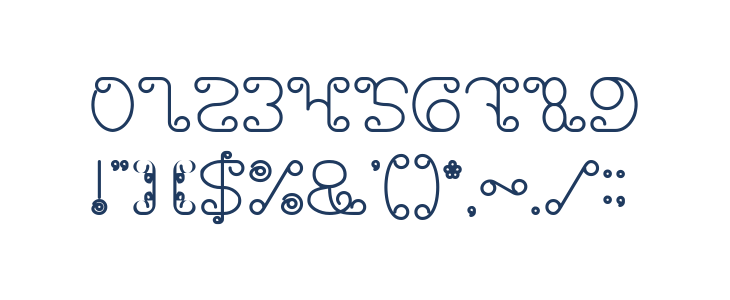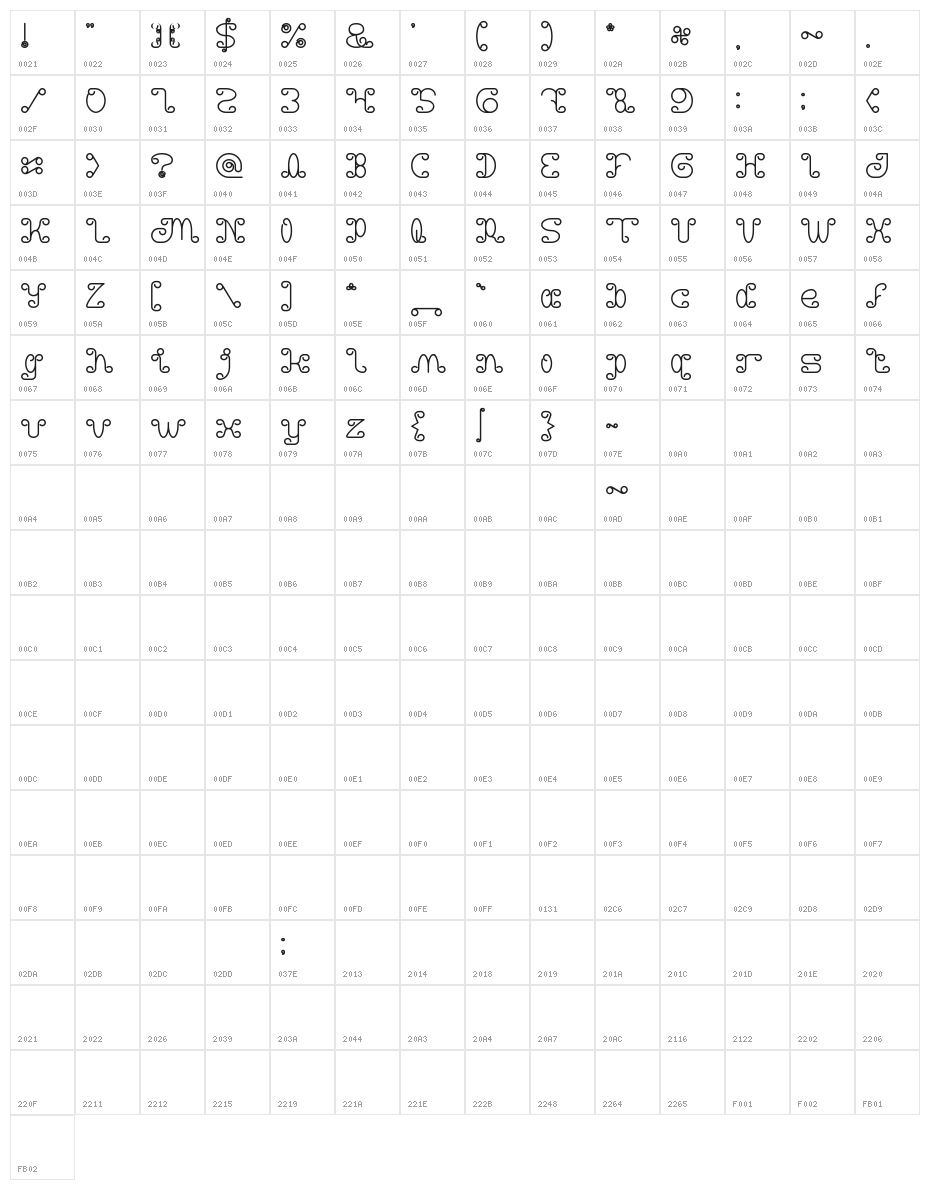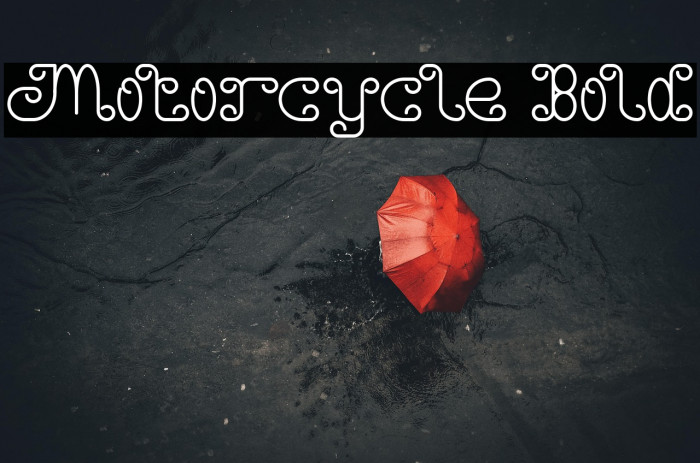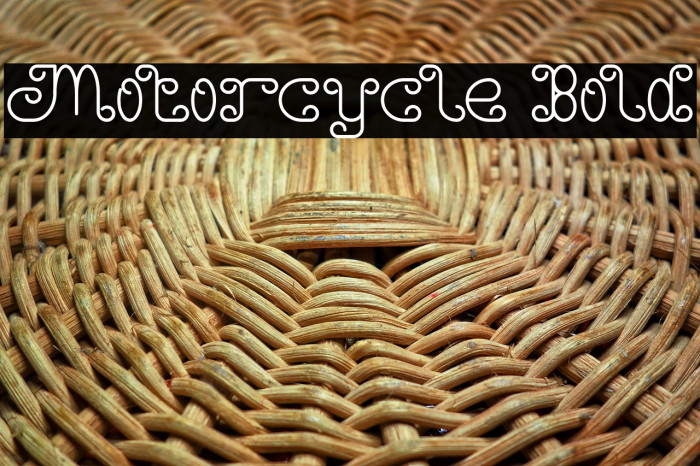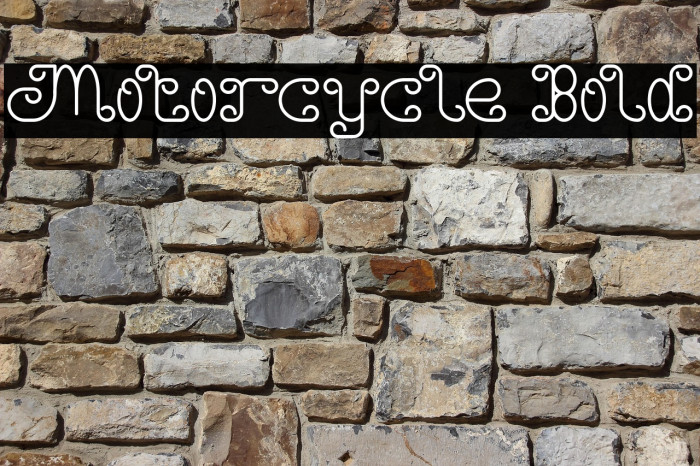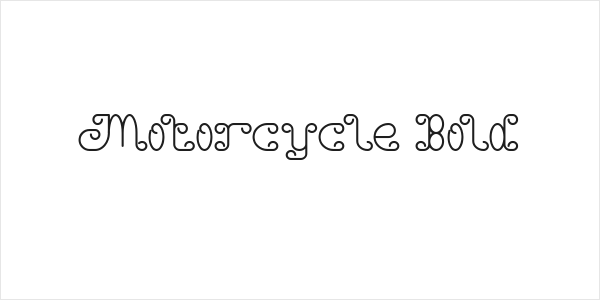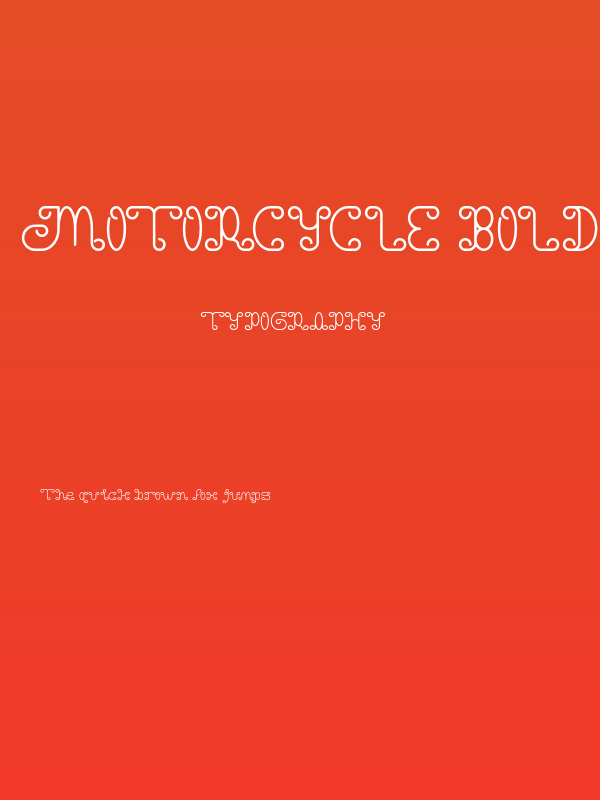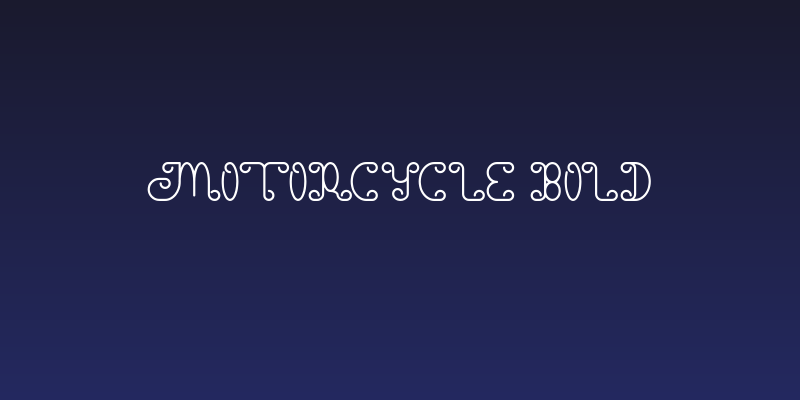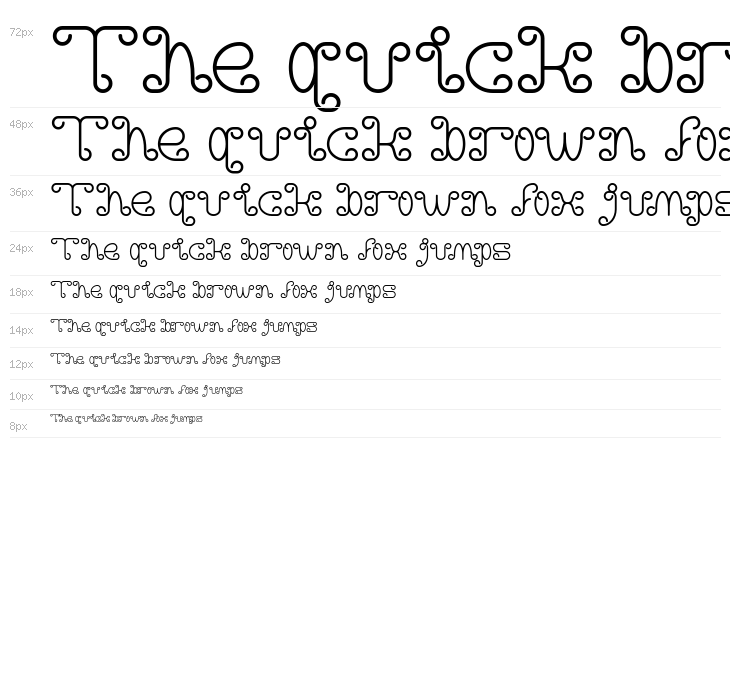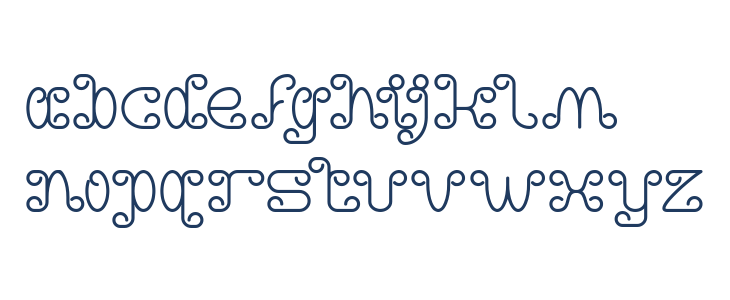
Motorcycle Bold Font
MOTORCYCLE-BOLD MAIUSCOLE
MOTORCYCLE-BOLD MINUSCOLO
MOTORCYCLE-BOLD ALTRI CARATTERI
| Nome | Motorcycle Bold |
| Caso d'uso | Logos, Posters, Invitations |
| Progetti proposti | Perfect for children's books, playful branding, creative posters, and artistic invitations. |
Motorcycle Bold